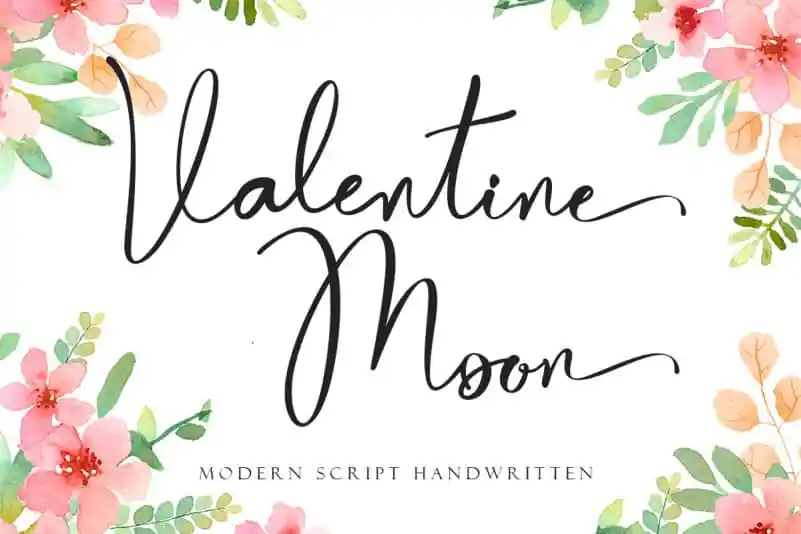
Valentine Moon Calligraphy Font – Download Grátis
A Valentine Moon Calligraphy Font é uma fonte única e encantadora que oferece uma experiência visual envolvente. Decorada com letras naturais e elaboradamente pensadas, esta fonte não só exala beleza singular, mas também permite que você use essas letras de maneira bastante simples e intuitiva. Com designs meticulosamente cuidados nos símbolos, a fonte é ideal para os mais diversos momentos: aniversários, bodas, convites, promoções nas redes sociais, apresentações e muito mais. É uma escolha perfeita tanto para criar experiências memoráveis quanto para estabelecer marcas sólidas de identidade visual em qualquer projeto.